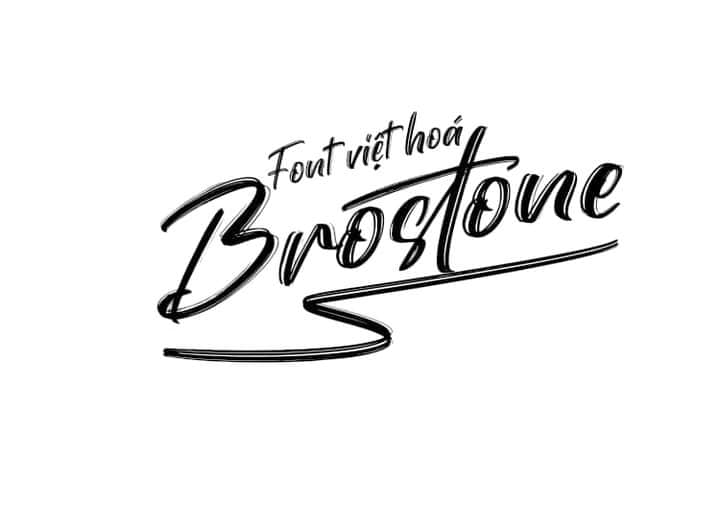
Giới thiệu về bộ Font việt hoá MJ Brostone – Brush
Trong thế giới đồ họa hiện đại, việc tìm kiếm một Font Chữ mang phong cách mạnh mẽ nhưng vẫn giữ được nét mềm mại là điều rất quan trọng. Font việt hoá MJ Brostone – Brush chính là giải pháp hoàn hảo cho những ai yêu thích phong cách cọ vẽ thủ công (brush style). Bộ font này được thiết kế với các đường nét phóng khoáng, tạo cảm giác tự nhiên và đầy năng lượng, phù hợp cho nhiều loại dự án nghệ thuật khác nhau.
Đặc điểm nổi bật của MJ Brostone – Brush
Bộ phông chữ này sở hữu cấu trúc ký tự độc đáo với những đường xước tự nhiên như được vẽ bằng cọ thật. Phiên bản Font việt hoá MJ Brostone – Brush đã được tối ưu hóa hoàn toàn bảng mã tiếng Việt, giúp người dùng dễ dàng gõ văn bản mà không lo bị lỗi hiển thị. Đây là lựa chọn tuyệt vời cho các bạn học sinh, sinh viên và giáo viên khi cần làm nổi bật tiêu đề bài giảng hoặc các poster sự kiện tại trường học.
Ứng dụng thực tế của Font việt hoá MJ Brostone – Brush
Nhờ vào diện mạo cá tính, bộ font này thường được sử dụng trong thiết kế logo, áo thun, bao bì sản phẩm hoặc các ấn phẩm truyền thông mạng xã hội. Sự kết hợp giữa nét chữ dày và phong cách brush giúp thông điệp của bạn trở nên ấn tượng và thu hút thị giác ngay từ cái nhìn đầu tiên.
Cách sử dụng font hiệu quả trong học tập
Khi sử dụng bộ font này, bạn nên kết hợp với các tông màu tương phản mạnh để làm nổi bật nét cọ. Tuy nhiên, lưu ý không nên dùng cho các đoạn văn bản dài để đảm bảo tính dễ đọc. Hãy thử nghiệm ngay để thấy sự khác biệt mà nó mang lại cho tác phẩm của bạn.
Kết luận về bộ phông chữ